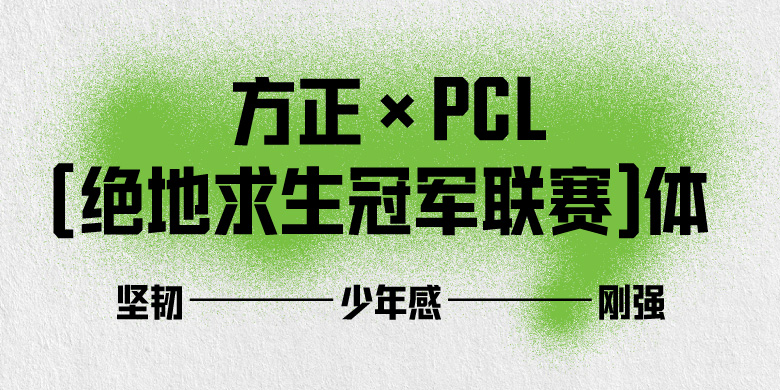
方正×PCL(绝地求生冠军联赛)体
方正×PCL(绝地求生冠军联赛)体,这款字体结构工整、笔画清晰,兼顾美观与易读性,适用于标题、正文、海报、包装、LOGO 等多种场景。字形优雅稳定,风格百搭耐看,适配日常排版与创意设计,让文字呈现更舒适、更具质感。方正×PCL(绝地求生冠军联赛)体一笔一画,皆是细节,以均衡的比例、流畅的线条打造舒适视觉体验,字形端正大气,风格简约现代。无论是商业设计、品牌宣传还是日常排版,都能轻松驾驭,让文字更有格调与力量。方正×PCL(绝地求生冠军联赛)体字体下载。
该字体”是由方正字库和绝地求生冠军联赛共同打造的一款充满少年感、具有团队协作精神、整体风格硬朗、性格刚强的创意黑体字。整体字形内部结构方正紧密、布白均匀、避让有序使字体拥有简洁干练、坚韧牢固的特点。与传统平切设计不同,此款字体将底部倾斜的笔画做了斜切处理,让笔画更加硬气、使字体具有书写感,同时增添昂扬无畏的少年气息。